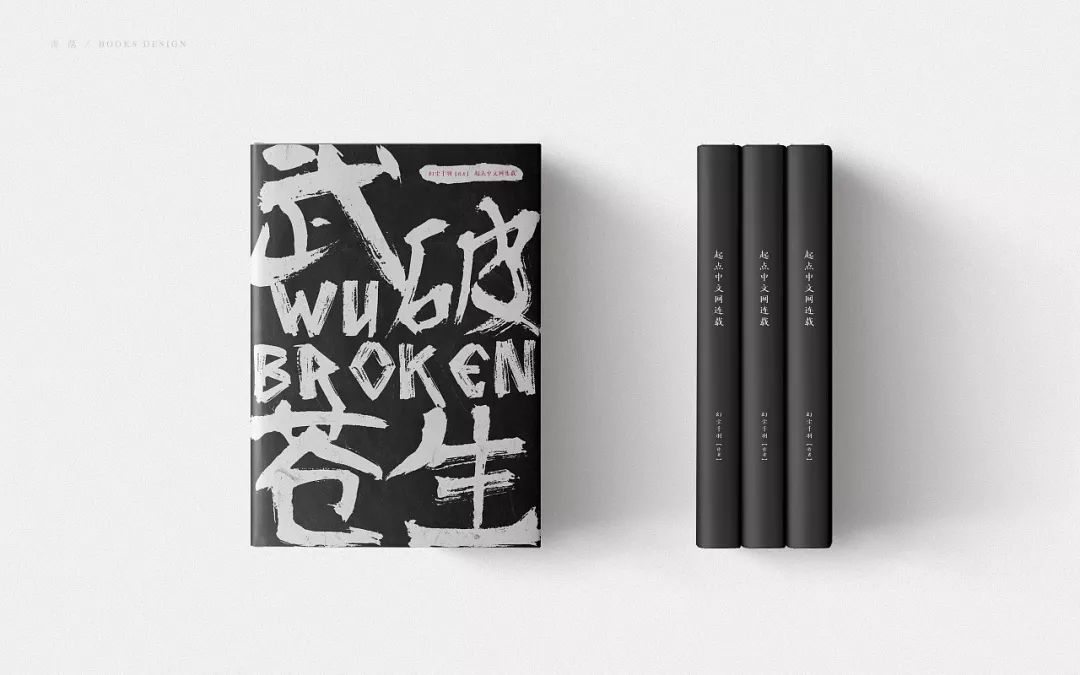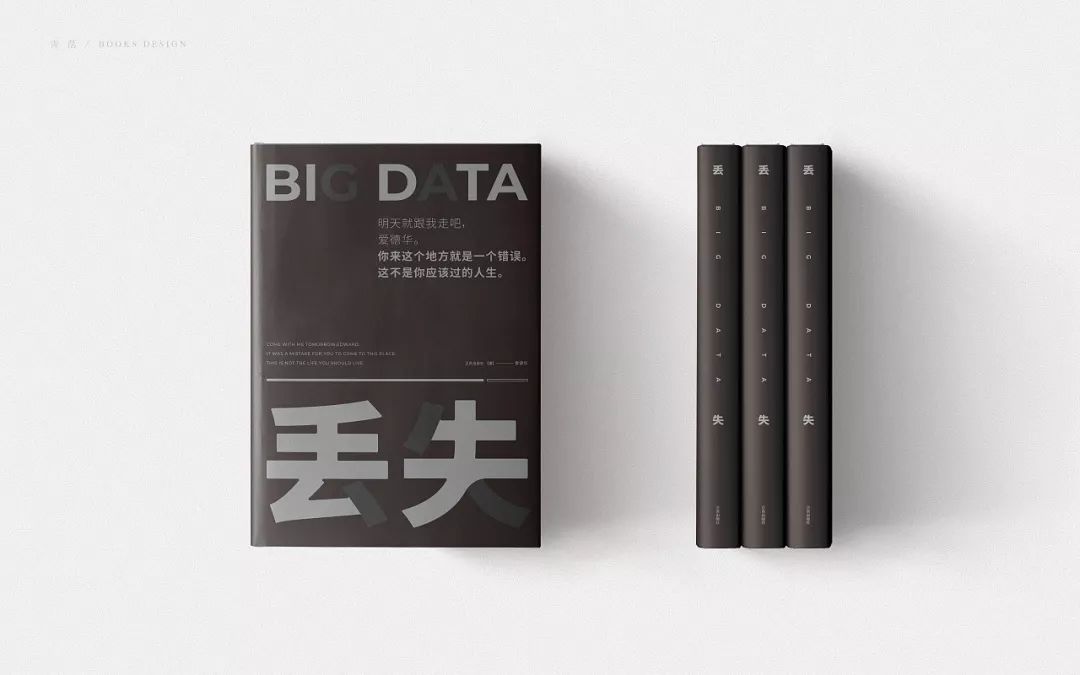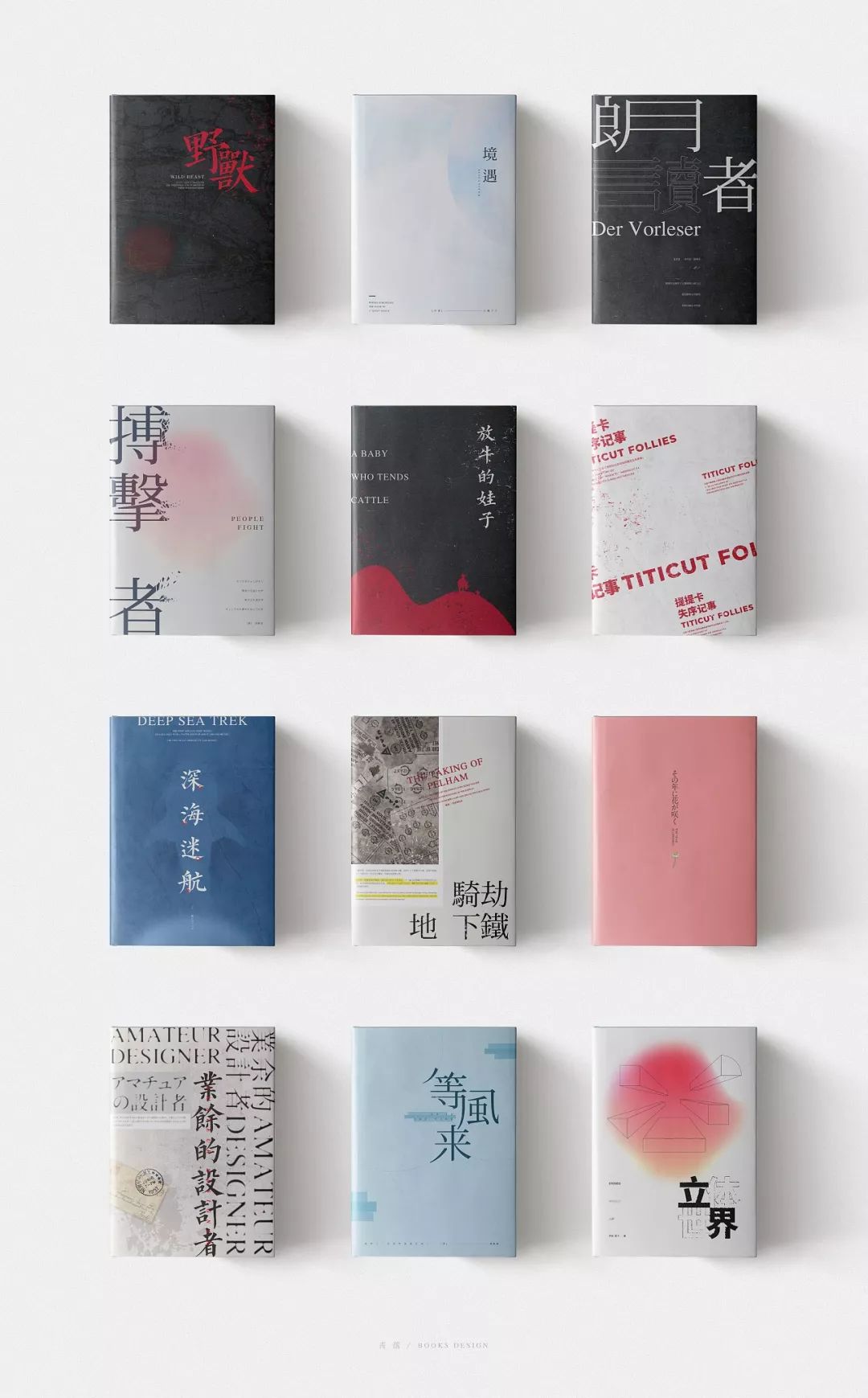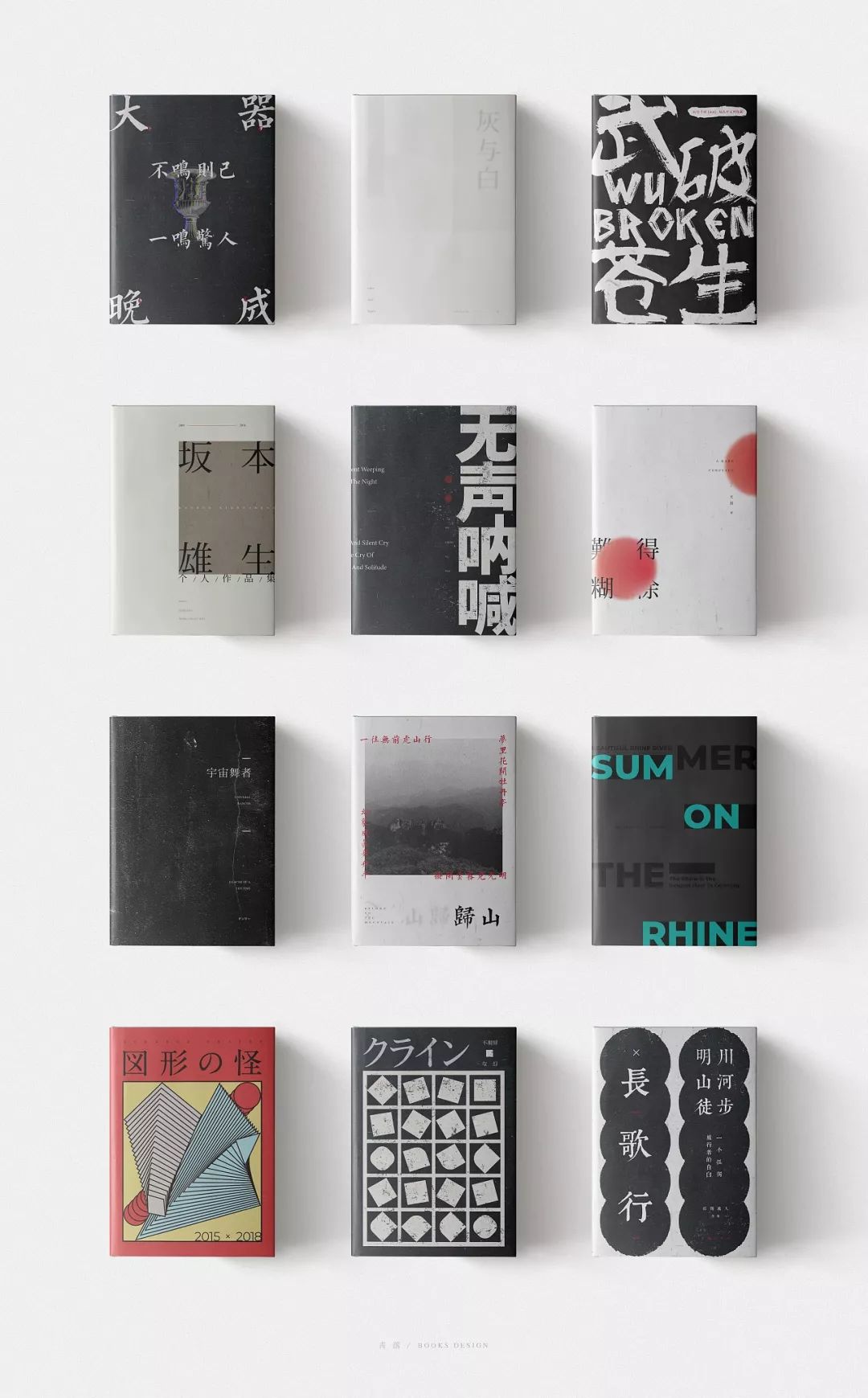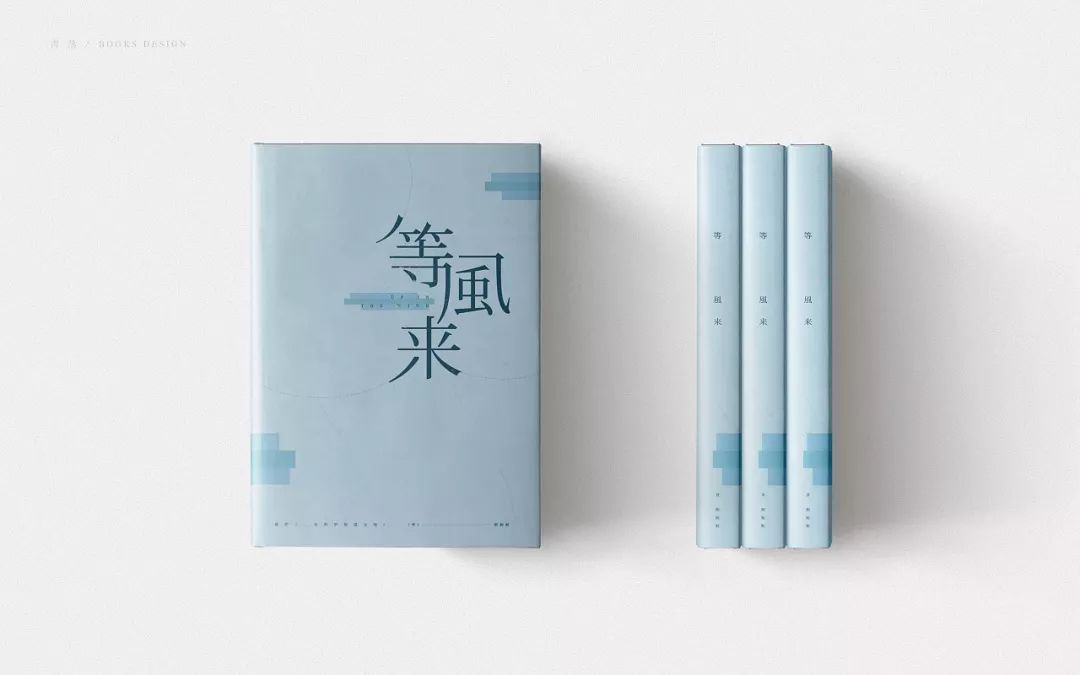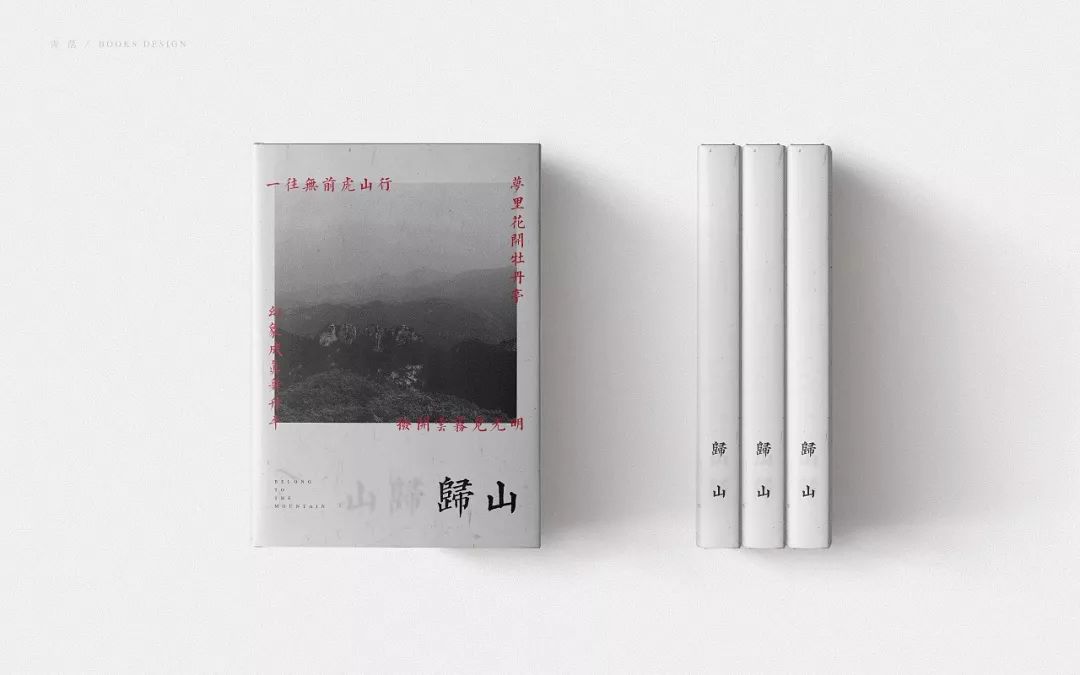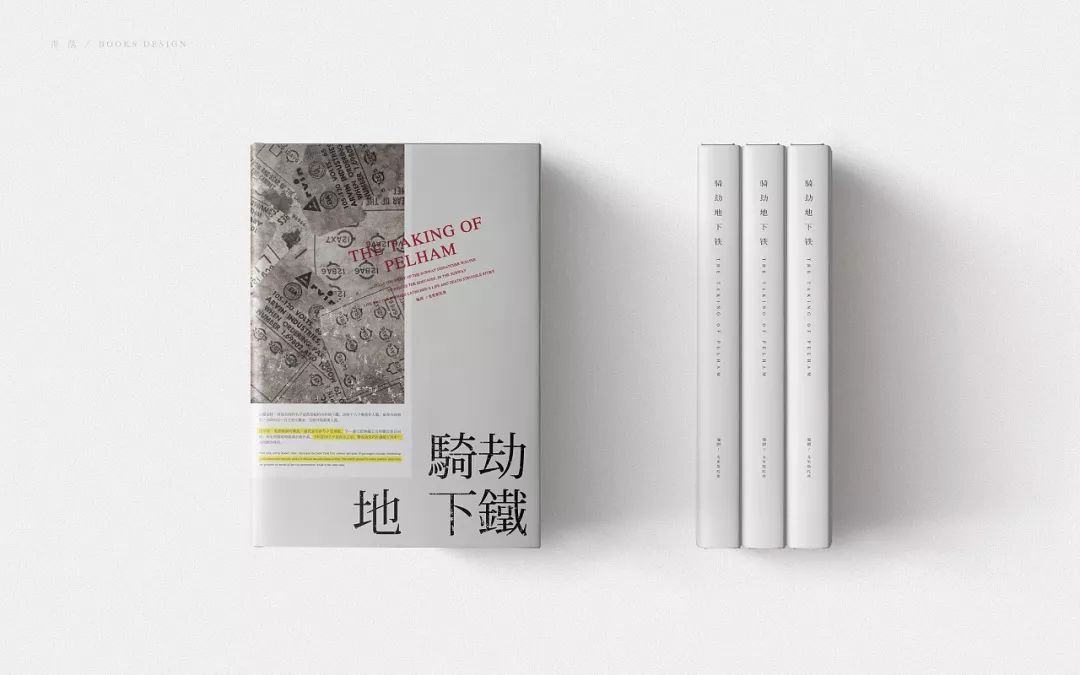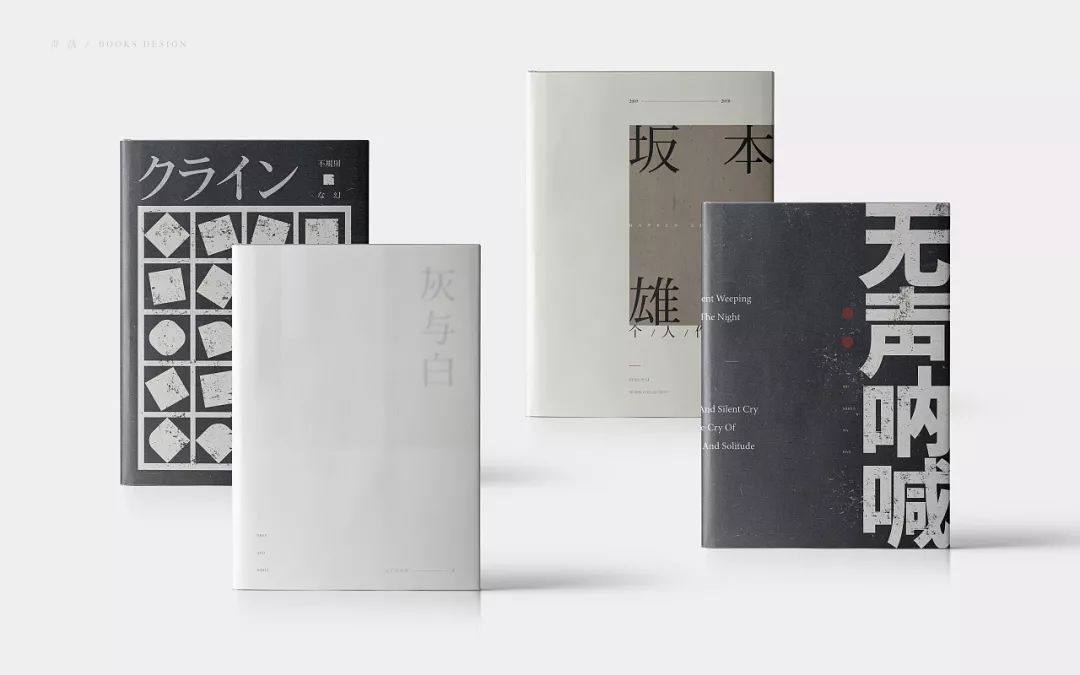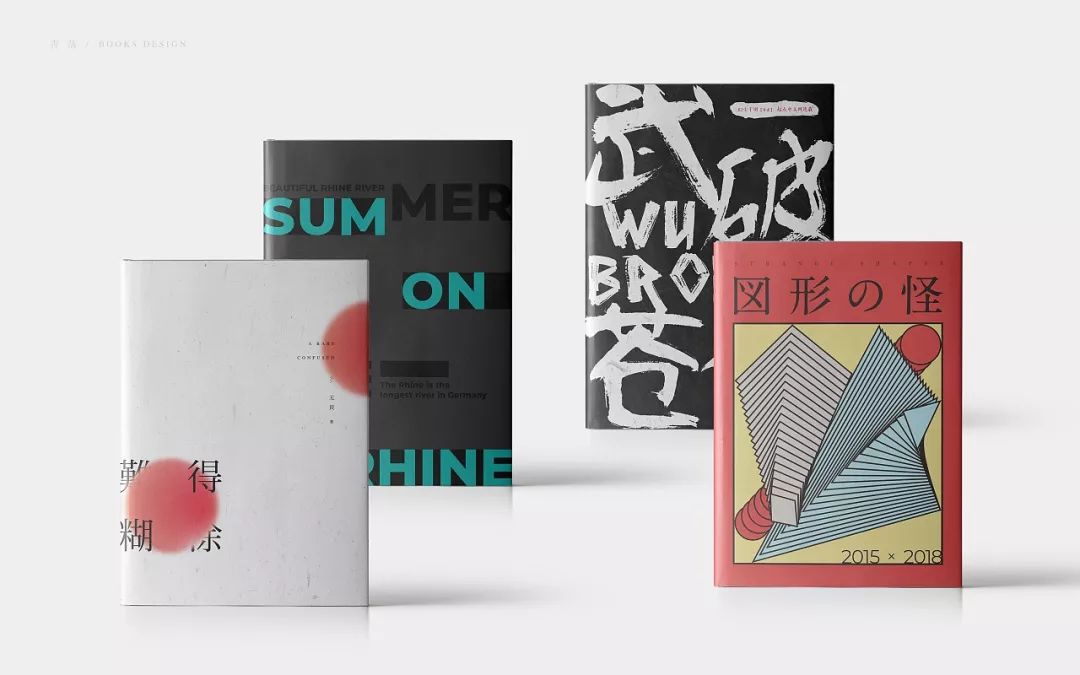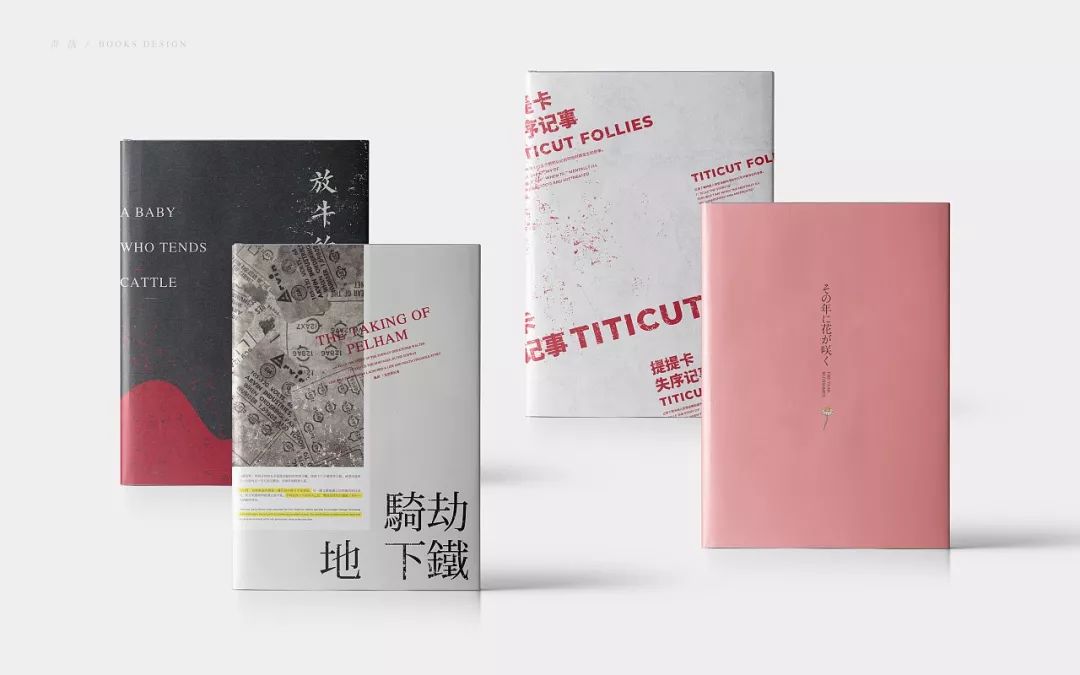
书籍封面设计分享,一个好的书籍封面,总能让读者一见钟情
常言道,书籍是人类进步的阶梯。
书籍服务于我们,在看书的过程中,书可以陶冶我们的情操。但再好的书也少不了一个吸引人的封面。所以作为设计师,应该为一本书设计最好的封面。
而设计师邹家东就做到这点。
邹家东设计的书籍封面,不仅仅只有图片与色彩,文字排版也是他设计的重头戏之一,毕竟没有哪一本书的书籍封面设计是缺少文字的存在的。封面文字中除书名外,均选用印刷字体,故这里我主要介绍书名的字体。常用于书名的字体分三大类:书法体、美术休、印刷体。
一起来看看他的作品:
书籍封面犹如刚出生的婴儿,开始新生,把读者引入到一个新的世界,新的起点。
一个设计师要以丰富的表现手法和内容,用视觉思维的第一印象推动人们拿起书籍的欲望。书籍的封面设计很重要。希望大家更要尽我们最大的努力设计出优秀的书籍封面,让读者一见钟情。